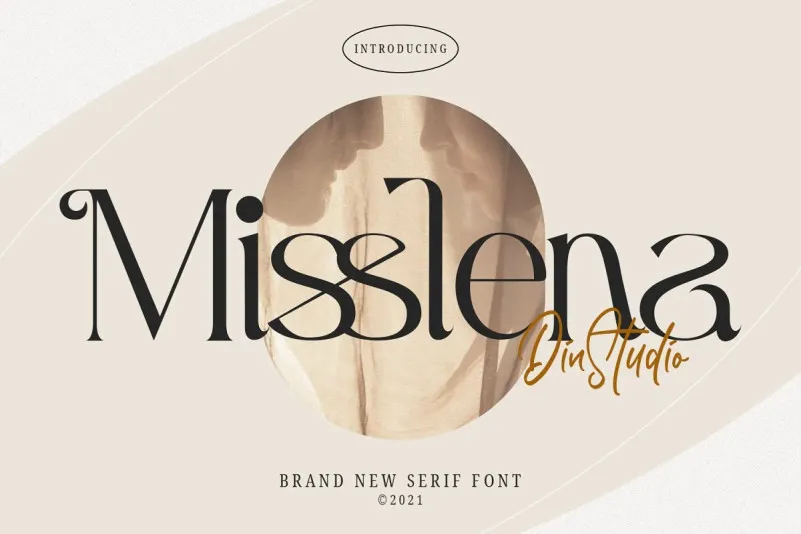
Misslena Font – Download Grátis
A Misslena Font é uma tipografia serif que oferece um ar clássico ao seu design, com traços mais salientes para um visual atraente e elegante. Desenvolvida pela Din Studio no site de criações 99designs, esta font contém letras maiúsculas e minúsculas, sinais gráficos e números. Além disso, inclui ligaturas e alternativas de caracteres que ajudam o texto a fluir naturalmente e adiciona uma sensação única ao seu logomarca ou cartão de visita. As versões mais leves desta font são ideais para o corpo do texto, proporcionando um equilíbrio harmônico. O recurso de alternativas estilísticas oferece um número variado de caracteres diferentes que dão uma aparência única ao seu projeto. Não perca esta oportunidade de dar um toque especial à sua identidade visual com a Misslena Font.